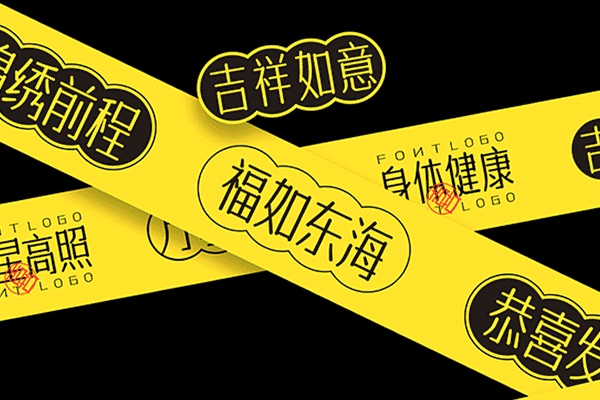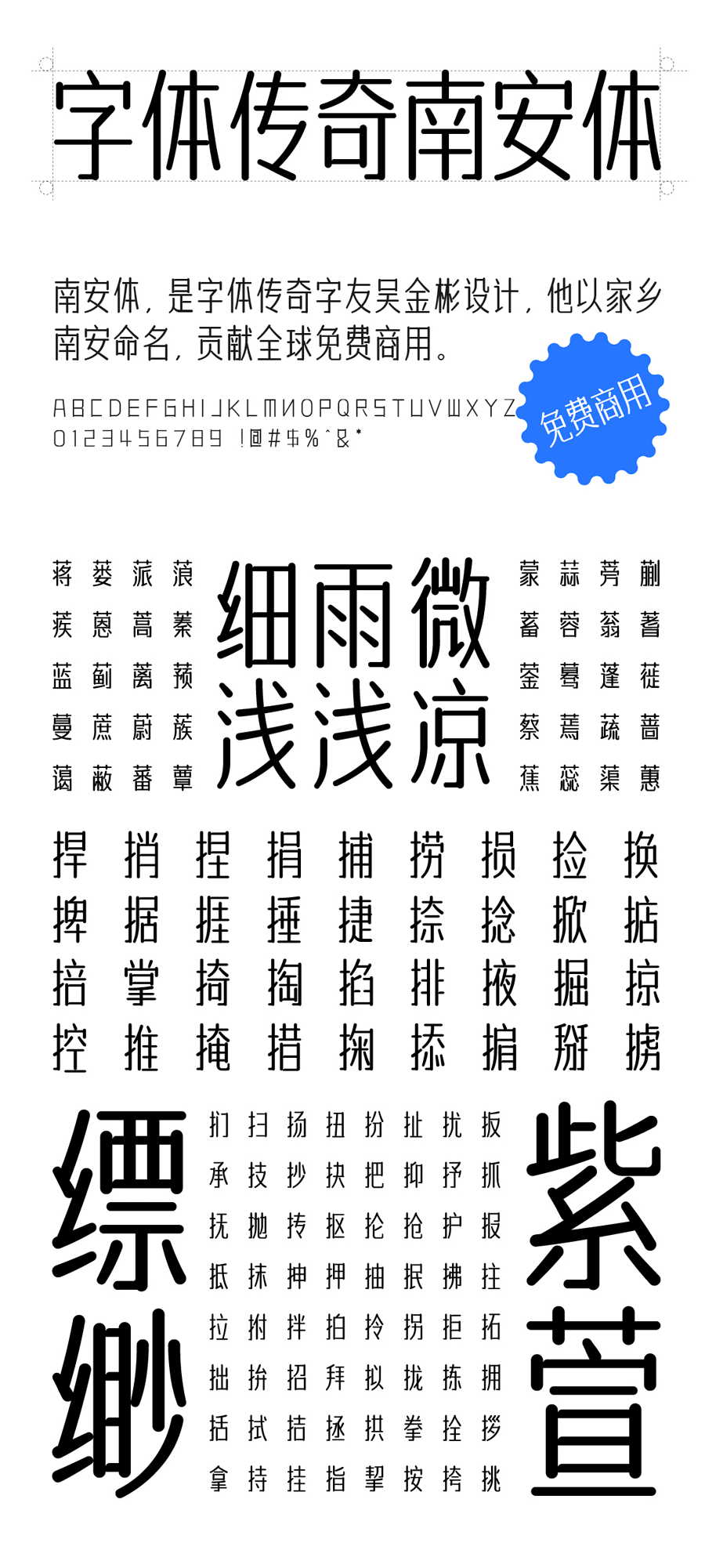
字体传奇南安体
字体传奇南安体是一款由字体传奇网(福建)字友吴金彬亲自设计的免费商用字体。这款字体以他的家乡南安命名,凝聚了他对故乡的情感与热爱。吴金彬希望通过这款字体,能够让更多人了解并记住他的家乡。
吴金彬在设计这款字体时,曾经历过很多困难和挫折。他曾坦言,自己兜兜转转N年后发现字库这一行非常符合他的需求,便决定投身于字体设计。作为一名维修工人,吴金彬对于设计方面的知识可谓一知半解,没有接受过专业培训。然而,他凭借坚定的决心和盲目的勇气,开始了自己的字体设计之旅。在面对种种困难时,他曾数次想要放弃,但最终还是选择了坚持。初稿完成后,吴金彬又对字体进行了反复修改和优化,整个过程耗费了他大量的时间和精力。
如今,字体传奇南安体已经包含了简体GB2312规范的6763个汉字,大家可以放心下载使用。这款字体不仅具有极高的实用性,还兼具美观性和易读性。无论是在商业还是个人用途中,它都能展现出独特的魅力。